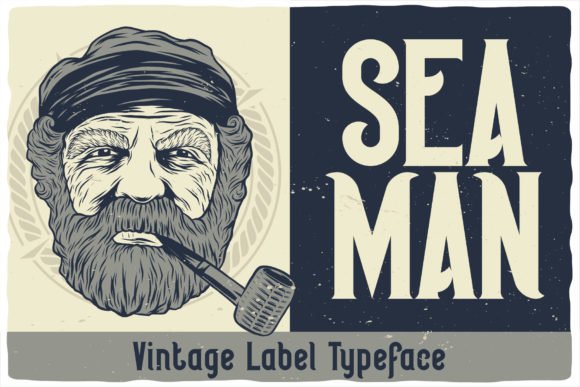
Seaman - это крутой, смелый и винтажный шрифт.
Независимо от темы, этот шрифт будет невероятно полезен в вашей библиотеке шрифтов, поскольку он способен приподнять любое творение.